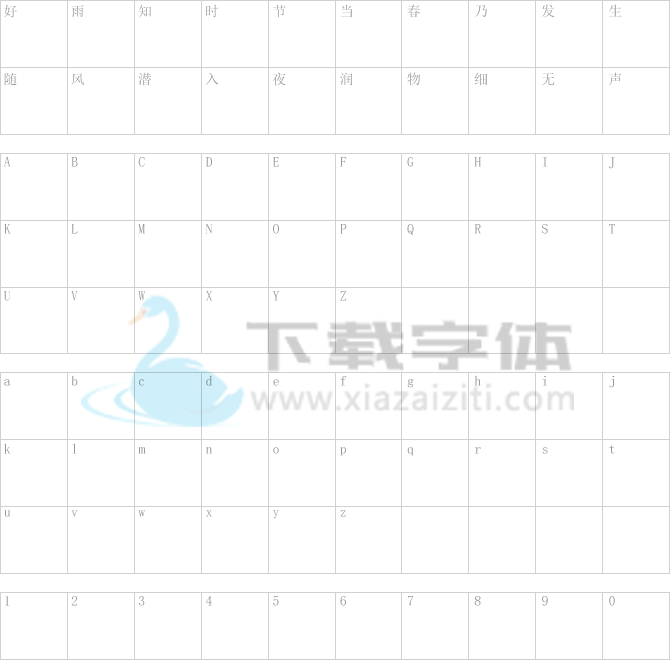
Auxiliary (Demo).ttf字体下载
Auxiliary (Demo).ttf字体下载,这款字体结构工整、笔画清晰,兼顾美观与易读性,适用于标题、正文、海报、包装、LOGO 等多种场景。字形优雅稳定,风格百搭耐看,适配日常排版与创意设计,让文字呈现更舒适、更具质感。Auxiliary (Demo).ttf字体下载一笔一画,皆是细节,以均衡的比例、流畅的线条打造舒适视觉体验,字形端正大气,风格简约现代。无论是商业设计、品牌宣传还是日常排版,都能轻松驾驭,让文字更有格调与力量。Auxiliary (Demo).ttf字体下载字体下载。